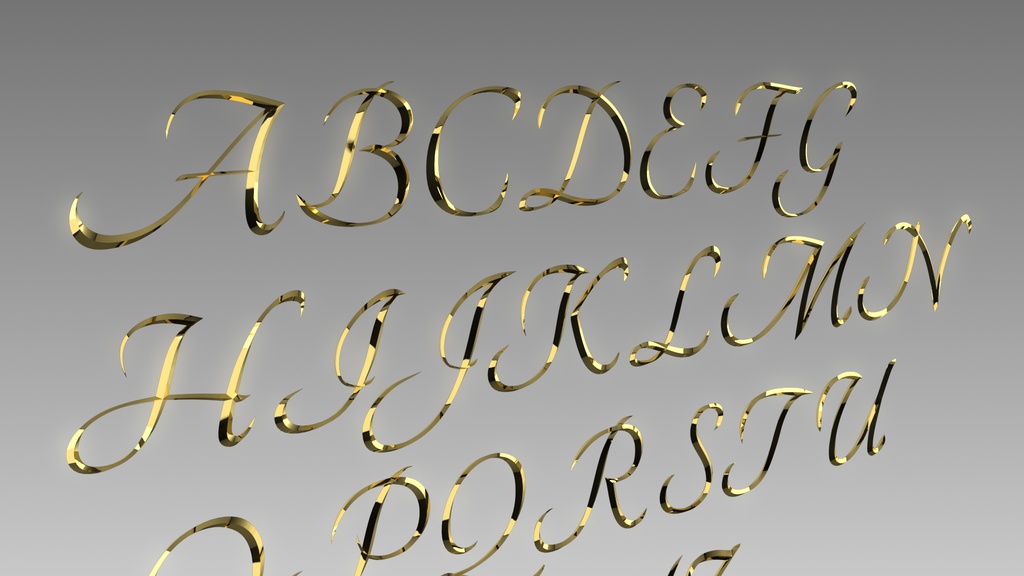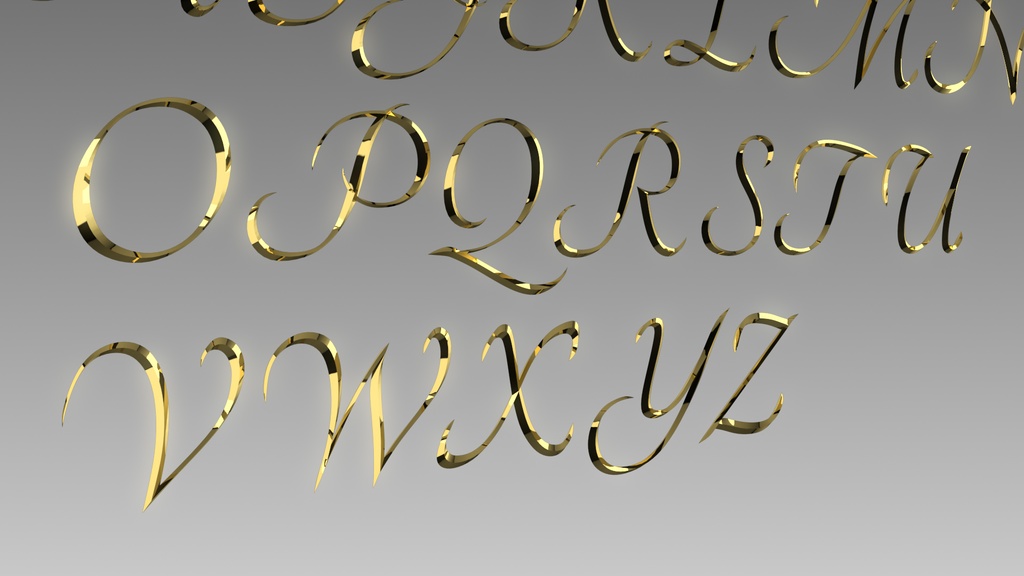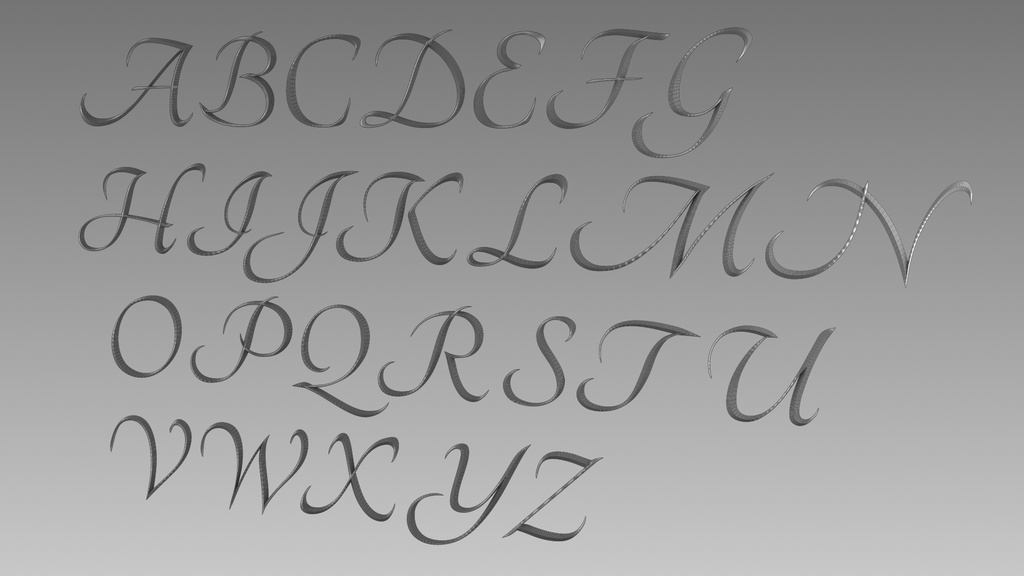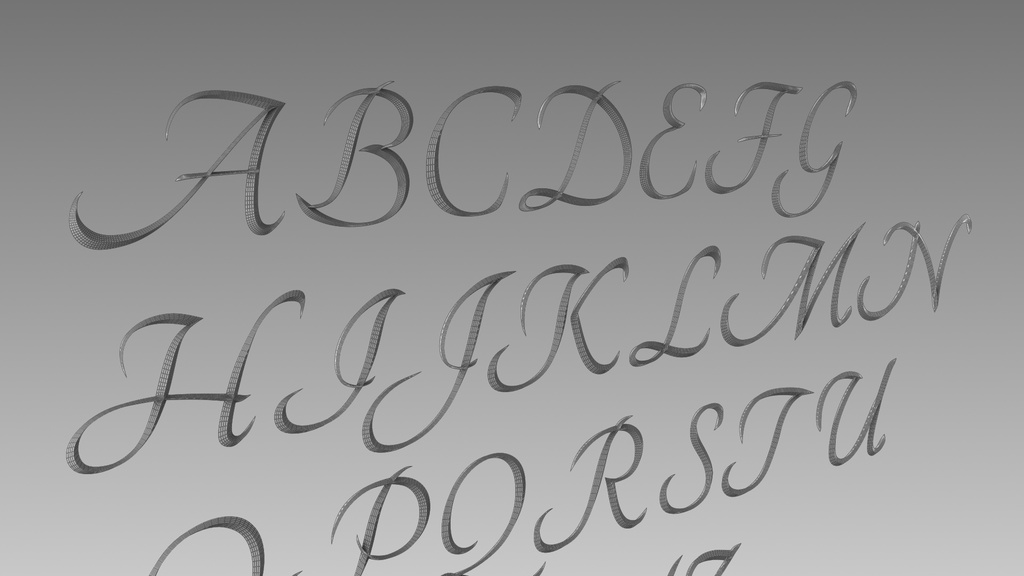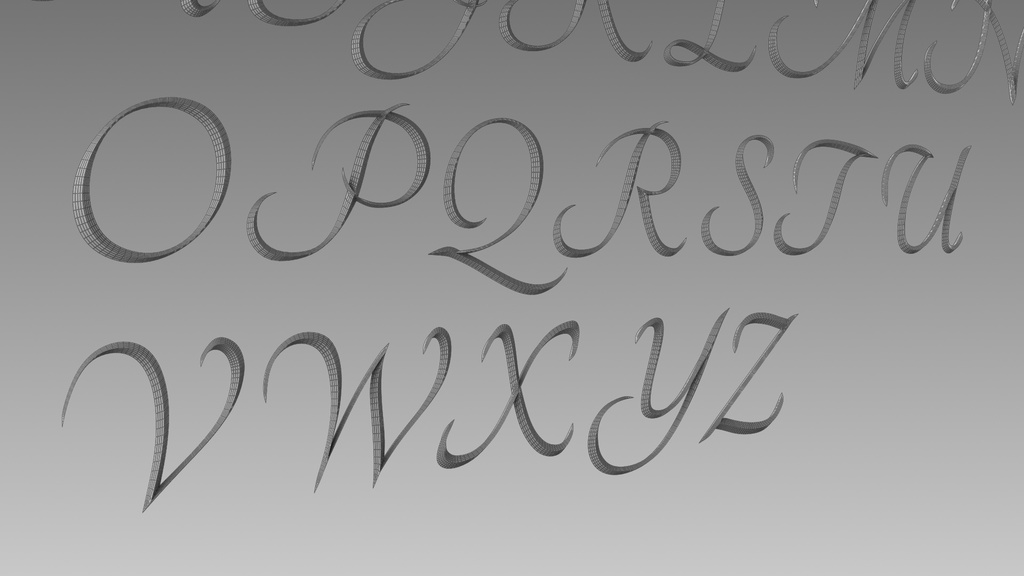
3Dフォントデータ 「AtoZ」
3Dフォントデータ 「A~Z」 FBX、OBJ形式の3Dデータです。 OBJも収録してあるのでElement3Dでも利用可能です。 単なる押し出しの文字ではなく表面も加工してありますので リッチな感じのタイトル作成が出来ます。 マテリアル、テクスチャ等は付いていません。 -利用規約- 本モデルを購入した時点で本規約に同意したものとします。 利用規約の内容は変更する場合があり、最新のものが適用されます。 ・商用・改変可 ただしモデル自体を販売することは禁止。 ・再配布は禁止。改変後も禁止 ・著作権表示不要。 ・特定の宗教、政治的主張目的での利用禁止。 ・本モデルデータを使用することによって何らかのトラブル・損失が発生しても当方は一切の責任を負いません。